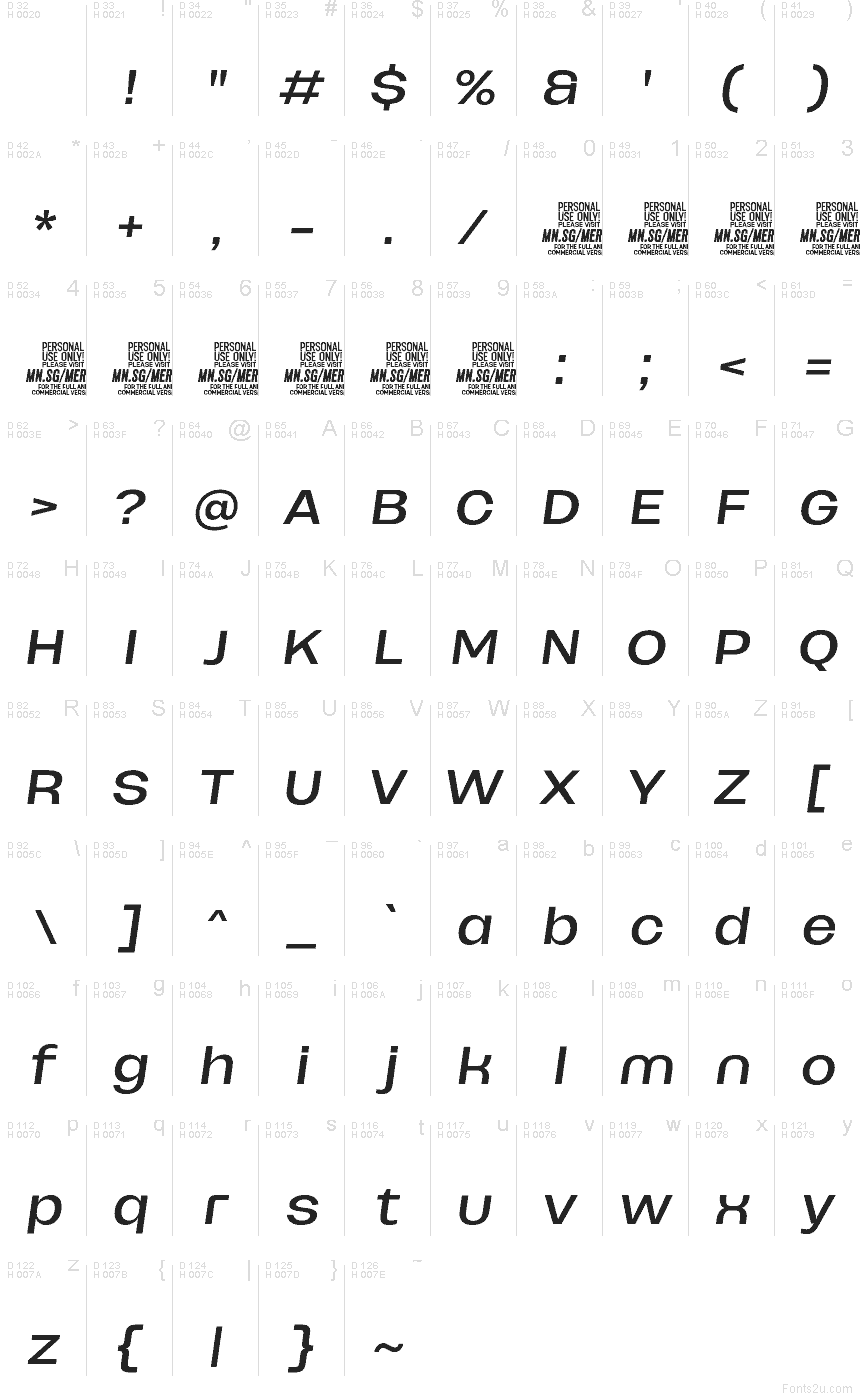
Merica Futurist, eine kostenlose, futuristische und kursive serifenlose Schrift von Mans Greback AB, setzt mit breiten, kräftigen Strichen, abgerundeten Verbindungen und einem dynamischen Schwung ganz auf Geschwindigkeit. Die Buchstaben wirken stromlinienförmig statt streng und verbinden geometrische Schlichtheit mit einer sportlich-technischen Ästhetik, die für ein flüssiges und markantes Schriftbild sorgt.
Die Schrift eignet sich ideal für Plakatüberschriften, Albumcover, E-Sports-Branding, Titelkarten und kurze Packungsaufschriften – überall dort, wo Bewegung wichtiger ist als jedes Detail. Als kostenlose Schriftart ist sie zudem perfekt für Logos, App-Splashscreens und prägnante Cover-Zeilen, da die schräge Silhouette und die weichen Ecken selbst kurzen Wörtern einen schnellen, technoiden Look verleihen.